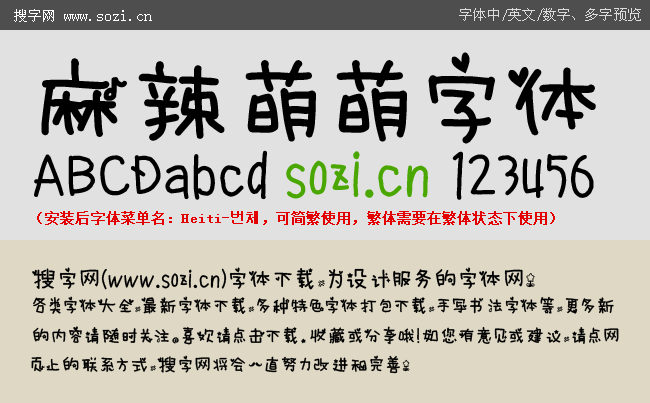
麻辣萌萌字體
搜字網(wǎng)給大家提供一款卡通手寫風(fēng)格的手機(jī)中文字體下載。名字叫麻辣萌萌字體,這款手機(jī)字體是仿照兒童手寫風(fēng)格的卡通手寫字體,結(jié)構(gòu)帶有POP字體風(fēng)格,字體間還插入有趣的卡通圖案,特別適合喜歡手機(jī)字體個(gè)性一些的朋友在手機(jī)上安裝使用。